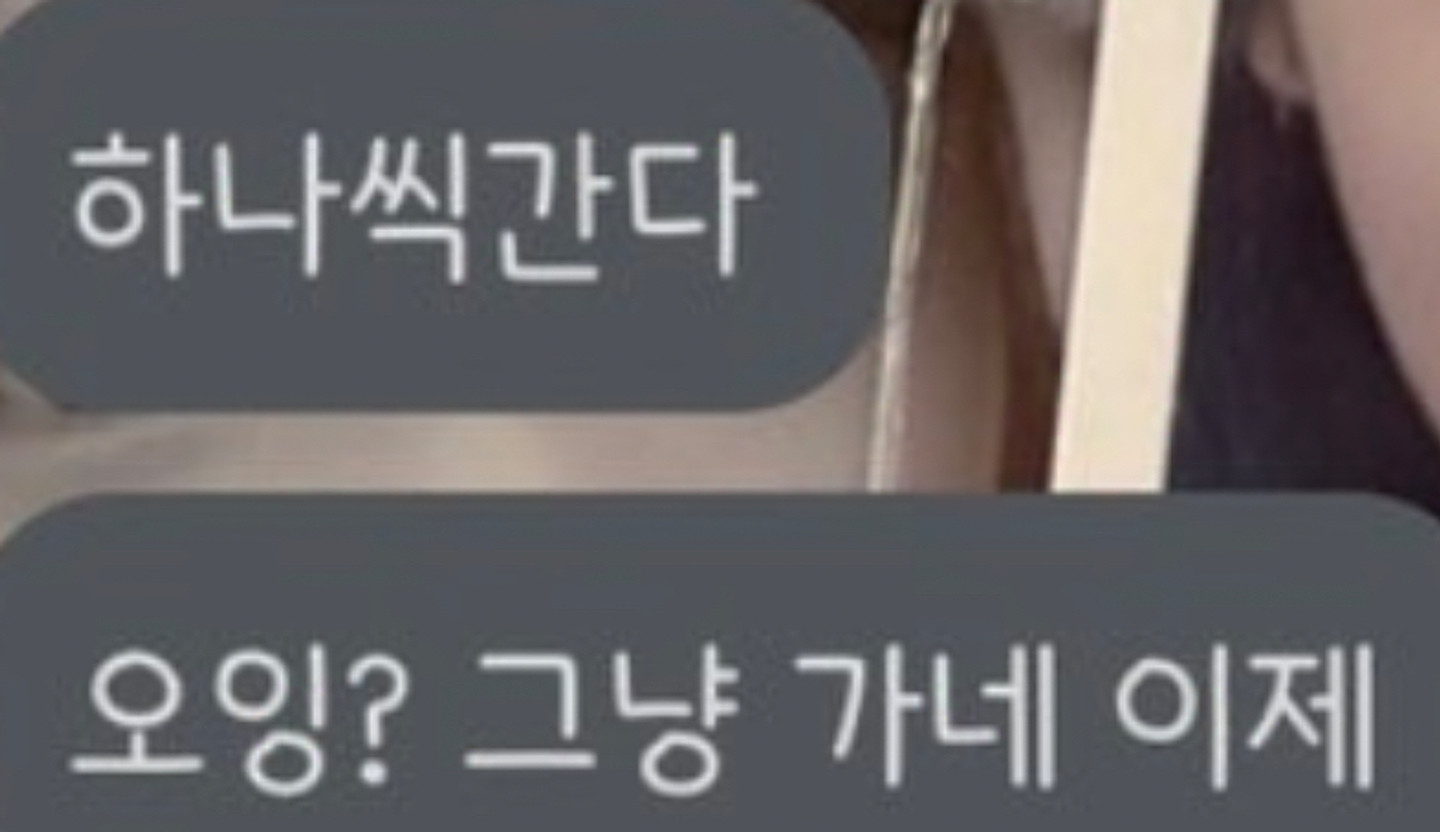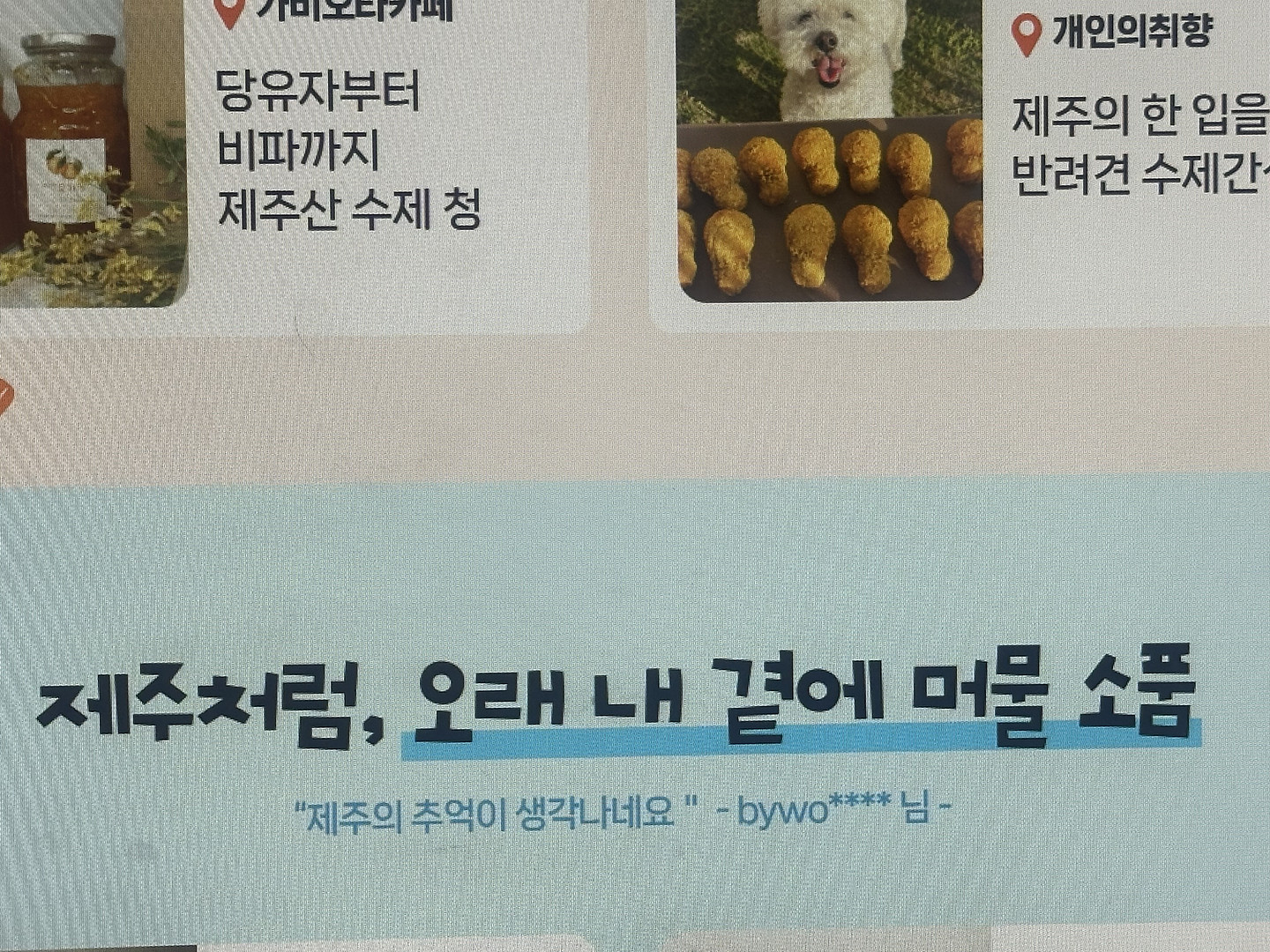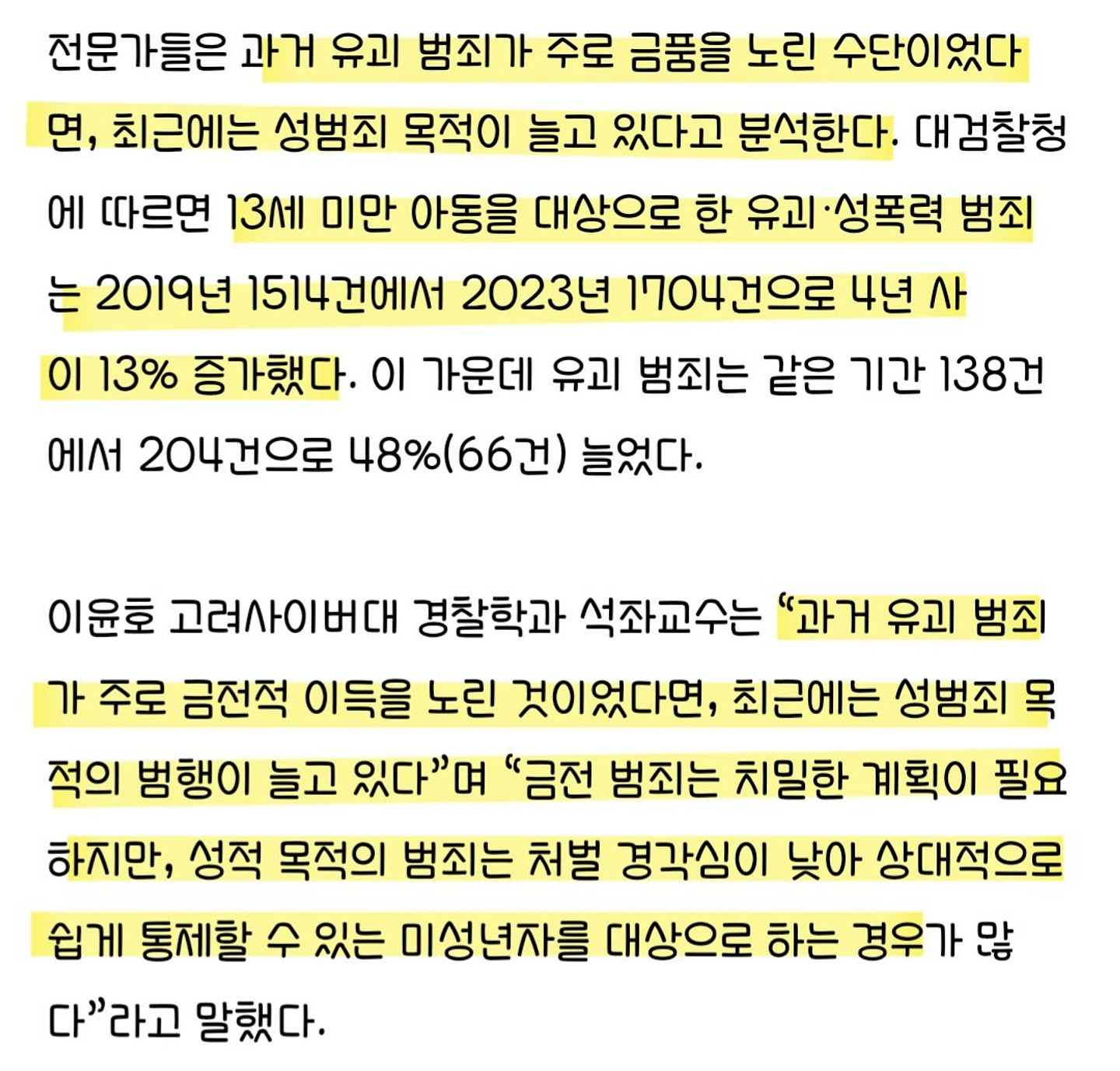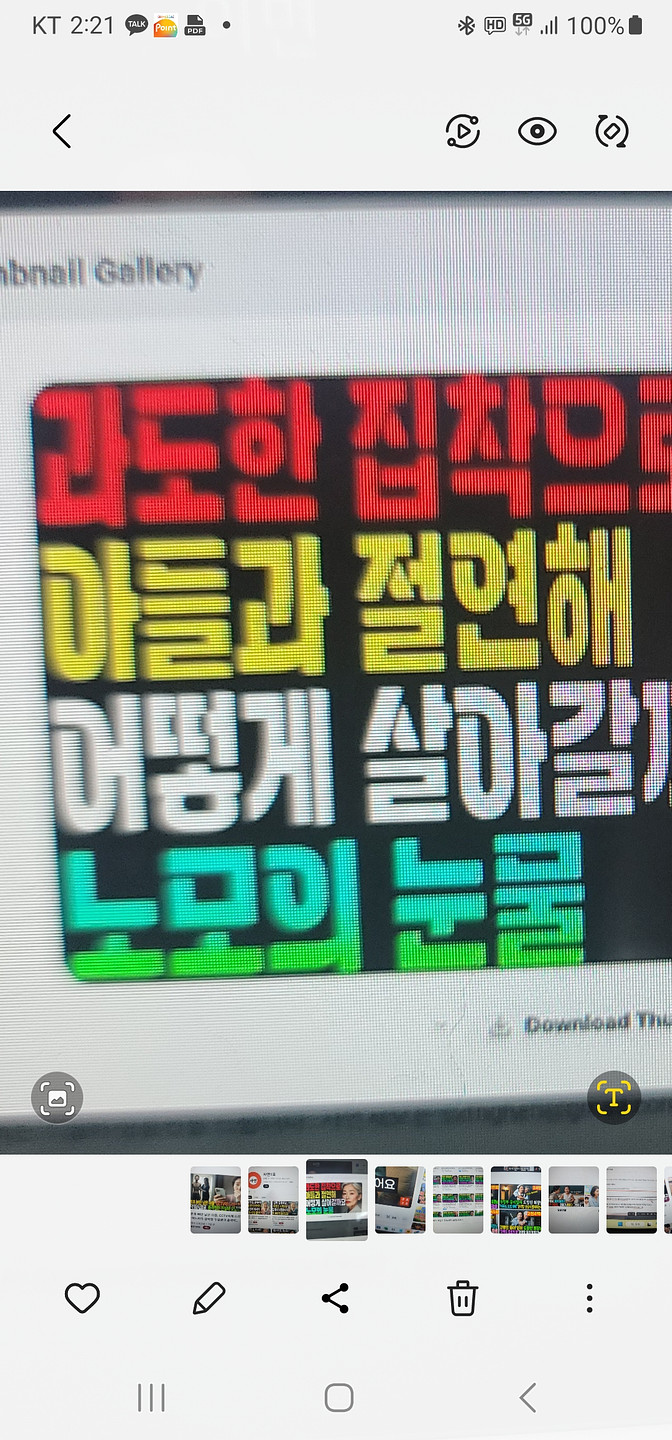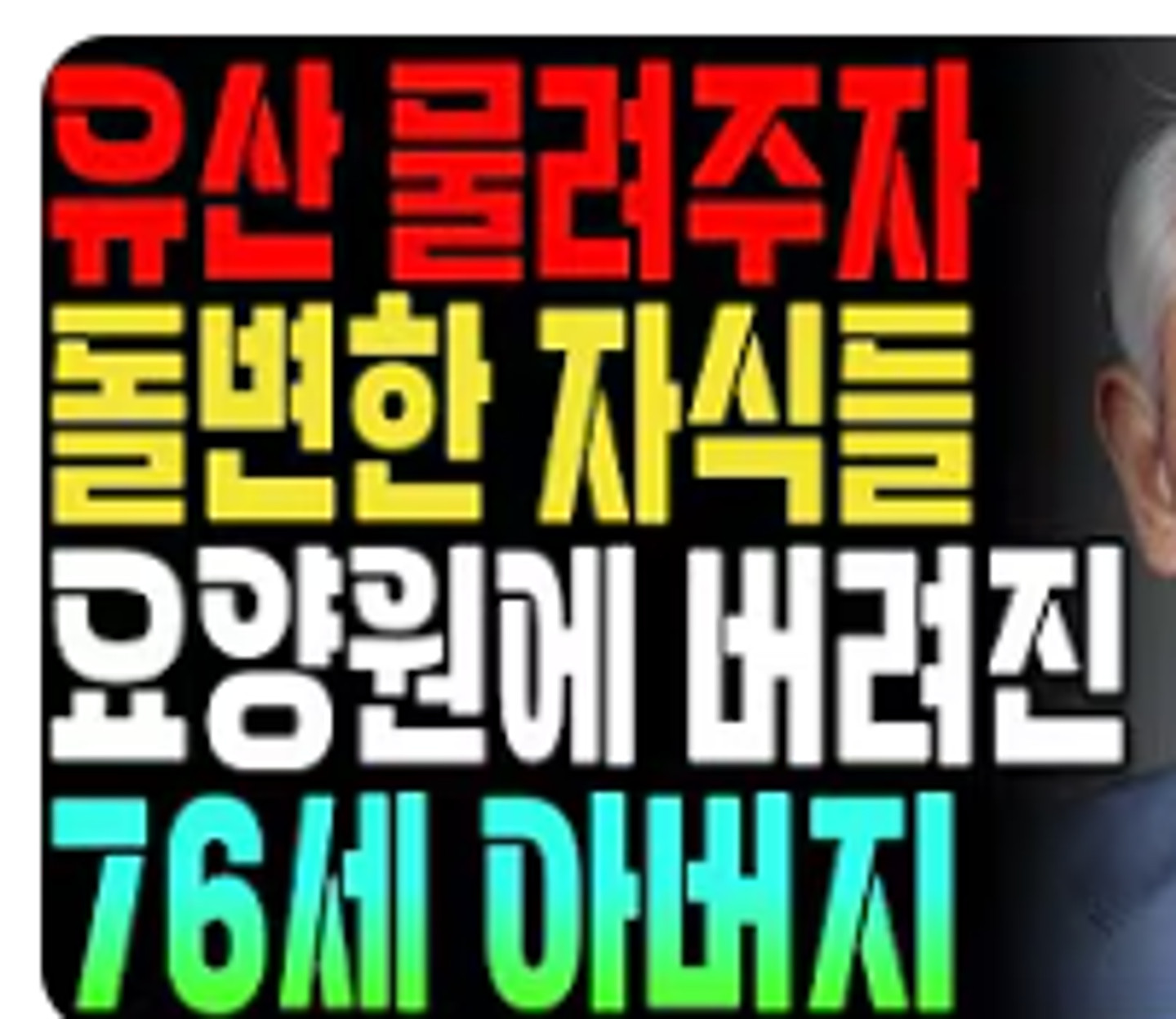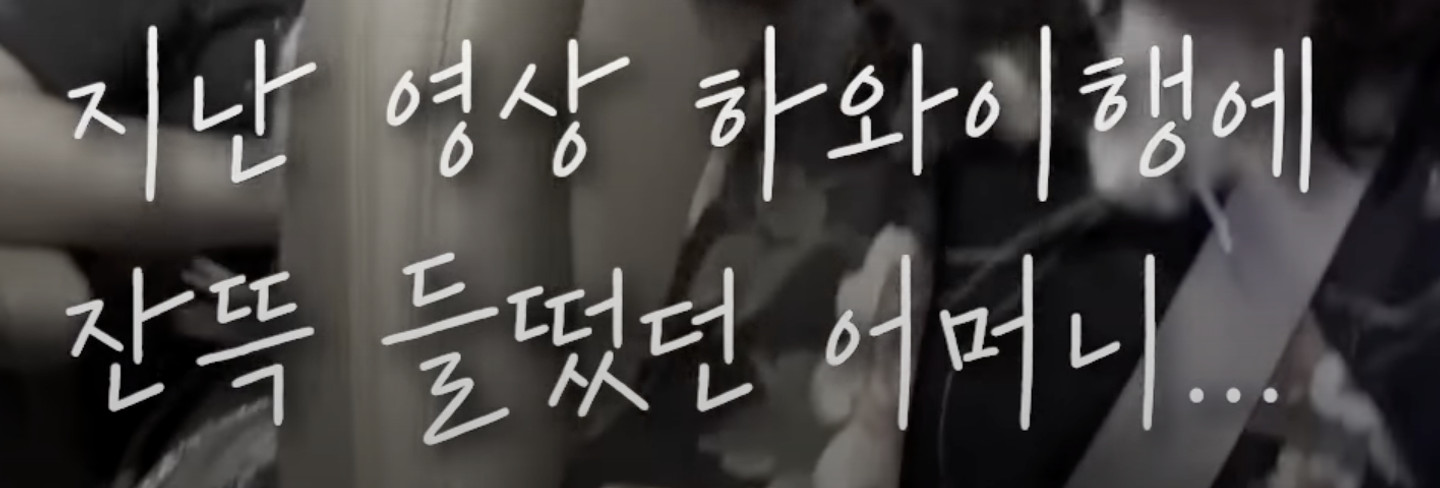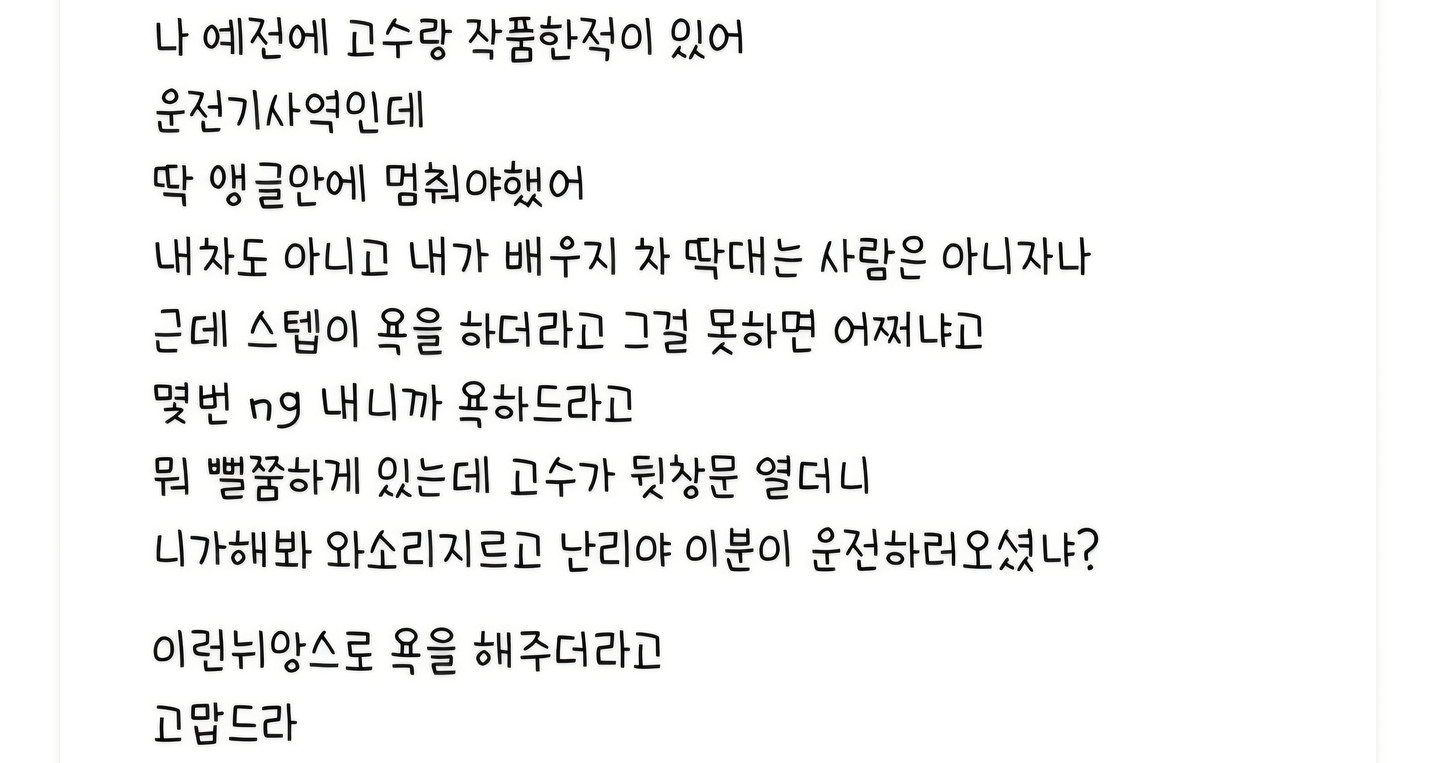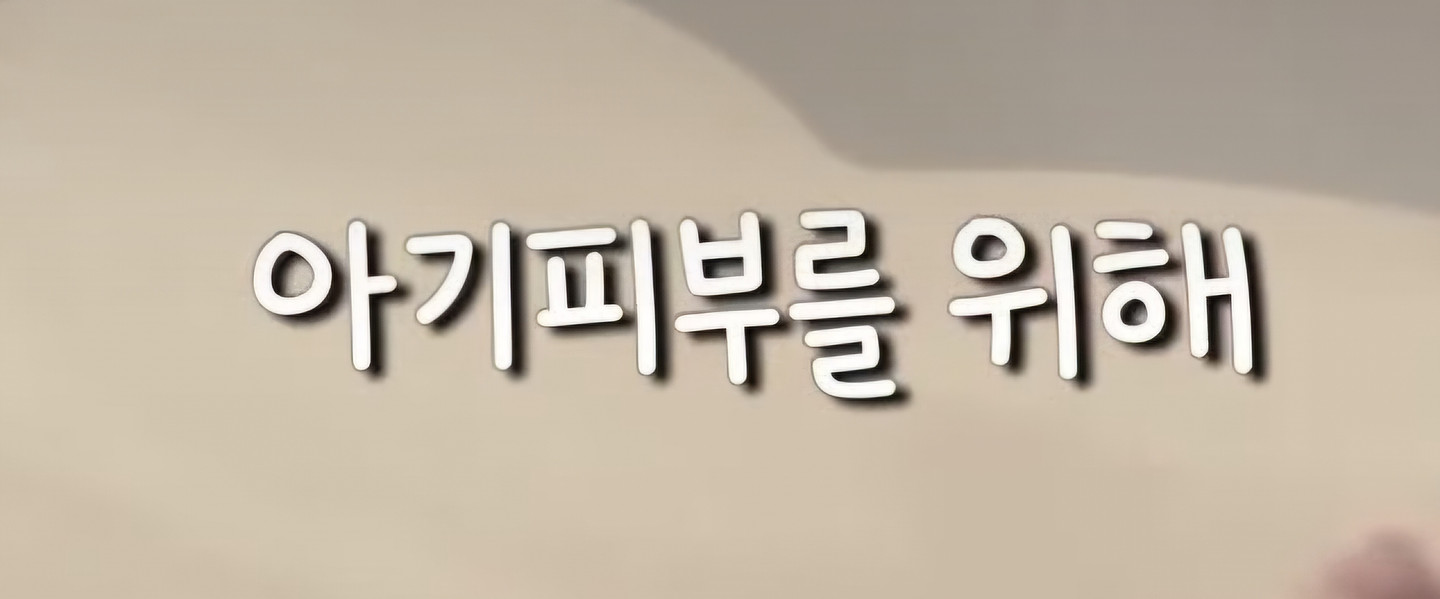
안녕하세요 !! 저는 신입 캡컷 크리에이터 인데여 캡컷 편집하는데 글꼴이 마음에 들어서 이걸 하고 싶은데 Ai는 자구 이상한 글꼴만 알려줘서 물어봐요 ㅠㅜ 제발 빨리 알려주세요 .. 저 이 글꼴 가지고싶어요 ㅠ ㅂ ㅠ
이 폰트 이름을 아시는 분 계실까요? 스파이더맨 브랜드 뉴 데이에서 타이틀 말구 영화 안에서 주로 쓰인 폰트입니다! ㅜㅜ 크레딧이랑 지역 이름 자막에 쓰였었어요! C, Q가 정원에 가깝고 t가 유독 가로가 짧아서 예쁘더라구요
광고보다가 발견했는데 요 폰트는 무슨 폰트일까요 ..? 해당 사이트 링크 https://shopping.naver.com/festa/onsale/pet/6a3dc98dae53687c6e16f5b3?dtm_source=naver_pcstockbottom&dtm_medium=mktatrb&dtm_campaign=2608-shopping-002&pcode=naver_pcstockbottom&campaign_id=2608-shopping-002&channel_id=naver_pcstockbottom&NaPm=nacn%3DghmZB0wd8a15